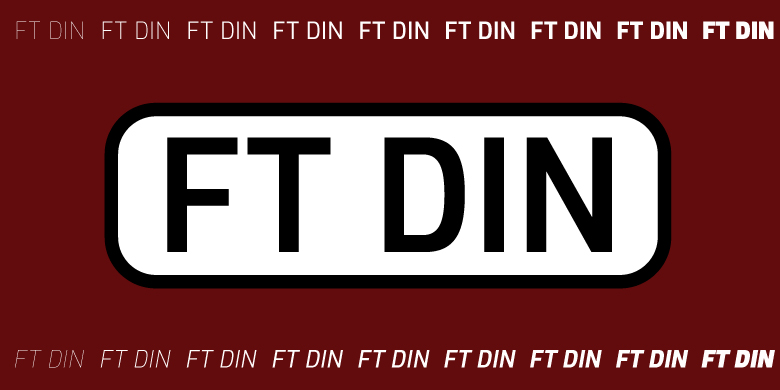
FTDIN
FT DIN是一款严谨,简洁,具有几何感的无衬线字体。FT DIN系列是在处理信息设计场景时的理想选择。在排版移动或桌面端应用程序、数据图表、数据可视化、UI、导视系统、交通标志、海报、标题,甚至可以使用在表情包中。FT DIN字体家族包括从Thin到Heavy共9档字重以及Roman和Italic两个样式。是在梳理大量复杂信息并进行可视化的得力工具。
二、设计特点
1.现代感:各个字母之间的比例相对均匀,这是现代风格对于各个字母宽度比例的要求。字母之间相关联的部件也进行了高度的统一化,增强的字体的一致性和统一性。
2.可读性:字体在细节处的设计决策有助于提升字体在段落中的易读性和易认性。如果字体需要在更苛刻的显示或者视觉环境下使用,可以通过OpenType特性来调取替换字形来满足易认性的需求。
3.泛用性:字体整体的风格相对中性、中立。可以在不同的题材和体裁的内容中使用。
4.独特性:字母的设计纠正了以往同类字体中的错误和不合理之处并使这些字母更符合FT DIN的设计理念。也使得这款字体在同类字体中具有其独特的特征。
5.多语言:字体目前支持使用拉丁文的270种语言。所需要的变音符号也进行了精心的设计和调整。并且针对特定的语言进行了本地化的调整以适应当地的视觉习惯。